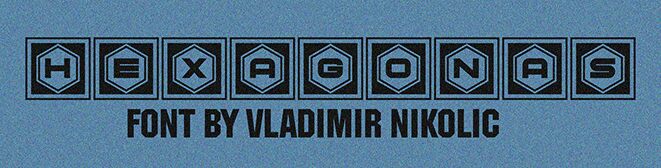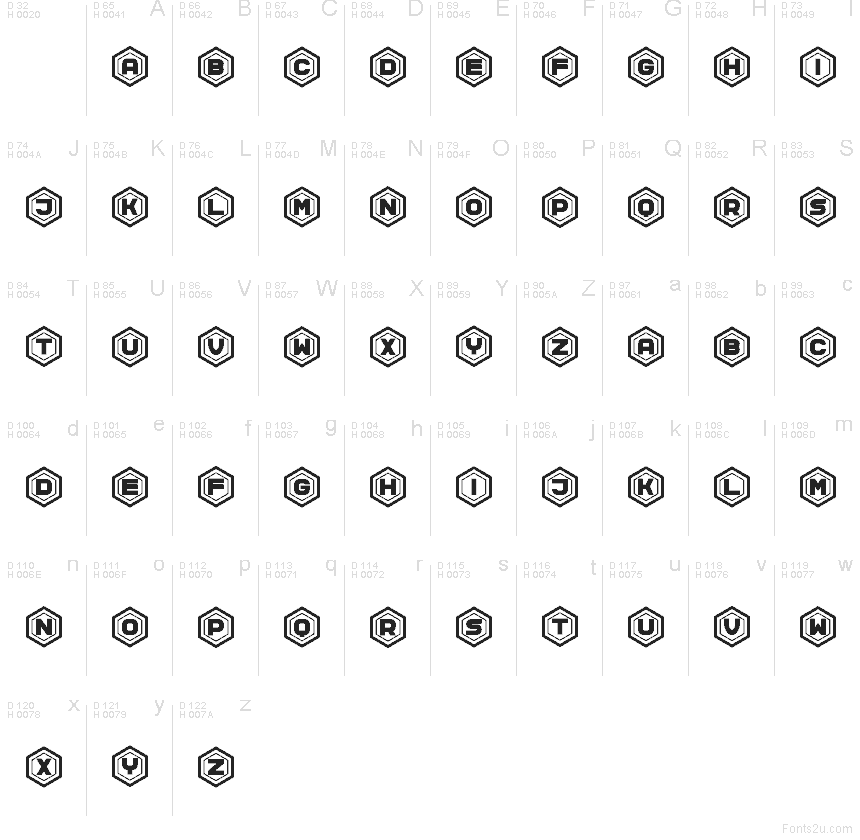
Hexagonas Flat Regular
La tipografía Hexagonas Flat de Vladimir Nikolic es una fuente decorativa gratuita construida sobre marcos hexagonales y formas de letras rectas y sólidas. El contorno repetitivo de seis lados dota a cada carácter de una estética de insignia, mientras que los centros abiertos y las esquinas definidas mantienen un diseño compacto y estructurado.
Hexagonas Flat funciona a la perfección en logotipos de videojuegos, etiquetas de ciencia ficción, títulos de carteles, insignias, iconos de aplicaciones y acentos de packaging donde un emblema geométrico sea el protagonista visual. Sus formas modulares consistentes la hacen ideal para iniciales de marca, gráficos de eventos y titulares ornamentales que requieran un ritmo nítido y cercano a la iconografía.